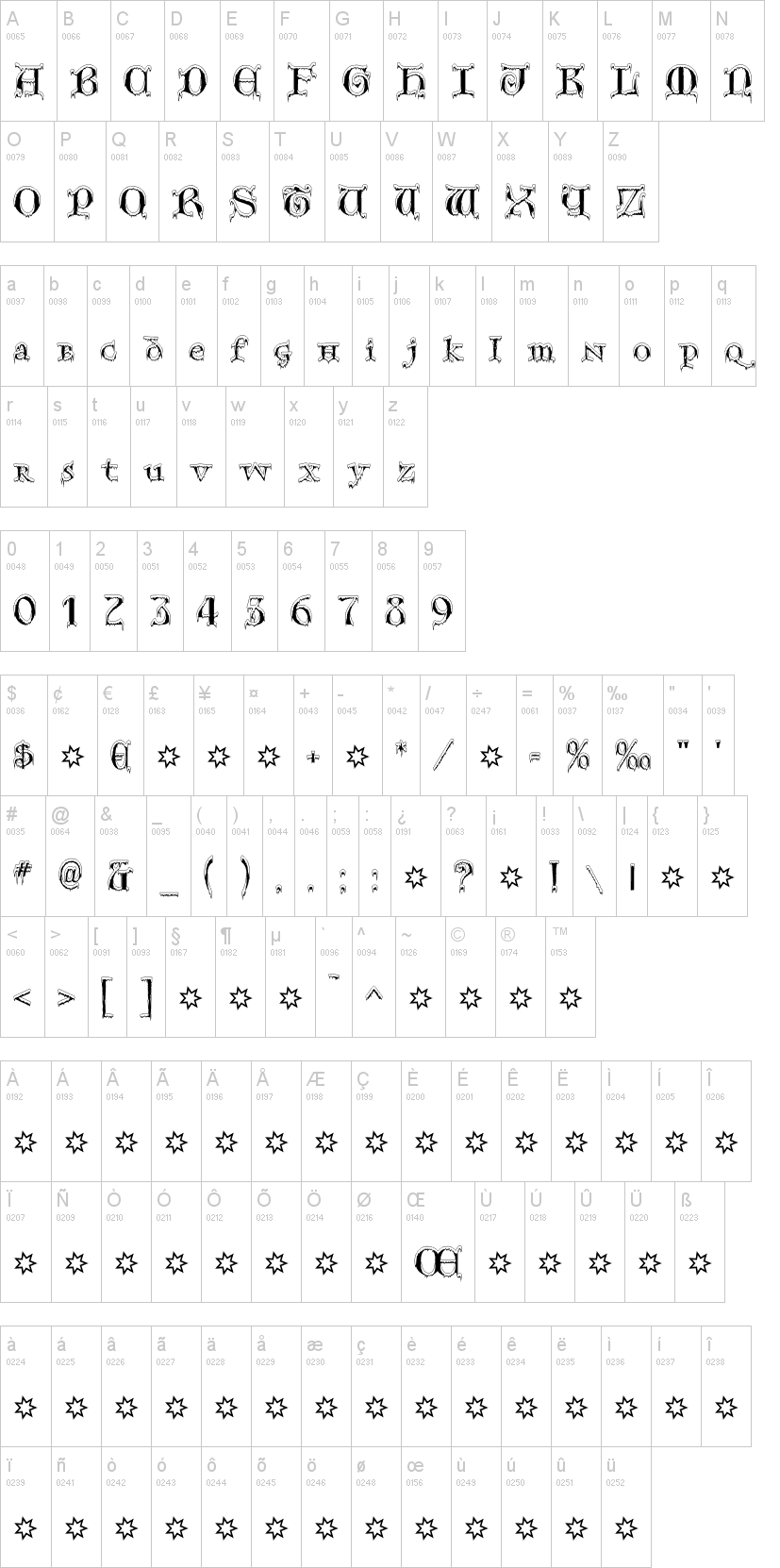
Generic Uncials SnowCapped 是一种古老的文字字体,它的特点是有一种粗体的、雪花状的线条,给它以独特的外观。它的字母形状被称为“uncials”,它们有一种轻微的卷曲,并且有一种温柔的质感。它主要用于装饰性的文字,如标题、标签和标语,也可以用于报纸、杂志和书籍的封面。它的灵感来源于古代的文字,但它的特点是它的粗体线条,具有独特的外观和感觉。内容介绍
Generic Uncials SnowCapped是一款非常不错的手写艺术字体,具有很好的视觉感,适合于文化类的宣传设计、商业类品牌的广告和产品包装设计以及个性化文字排版等较多场景。